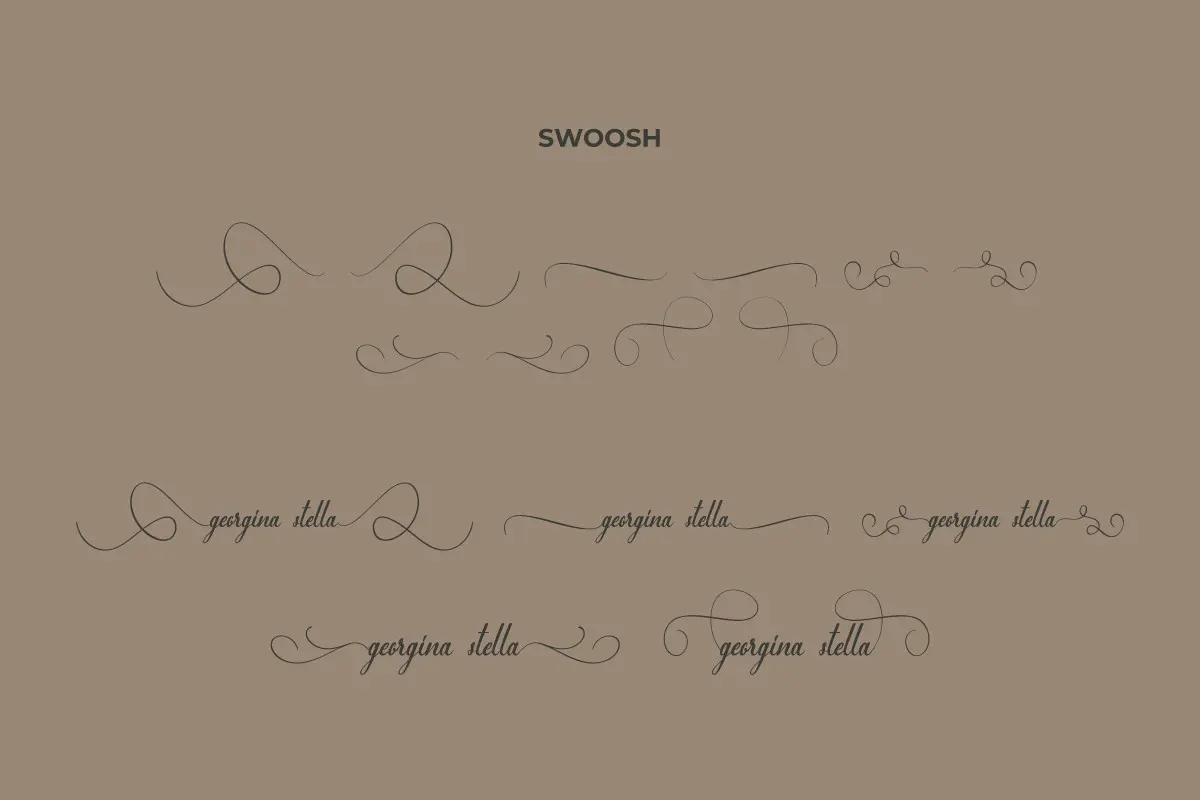
فونت سرهم رمانتیک و عاشقانه
فونت Georgina Stella یک فونت دست نویس زیبا و ماندگار است که با سبک ظریف و کلاسیک خود، جلوهای خاص و چشمگیر به نوشتهها میبخشد. این فونت بهترین انتخاب برای طراحی لوگوهای جذاب، برندینگ حرفهای و نقلقولهای هنری است. همچنین به دلیل PUA Encoded بودن، دسترسی به تمامی گلیفها و سوئشها بهسادگی امکانپذیر است.
- طراحی دستنویس زیبا و کلاسیک
- مناسب برای لوگو، برندینگ و نقلقولهای هنری
- دسترسی کامل به گلیفها و سوئشها با PUA Encoding
- جلوهای خاص و برجسته برای نوشتهها
- طراحی لوگوهای حرفهای و چشمگیر
- ساخت کارتهای دعوت و تبریک
- استفاده در برندینگ و کارتهای ویزیت
- طراحی پوسترها و نقلقولهای هنری
- افزودن به پورتفولیو طراحان گرافیک و تایپوگرافی